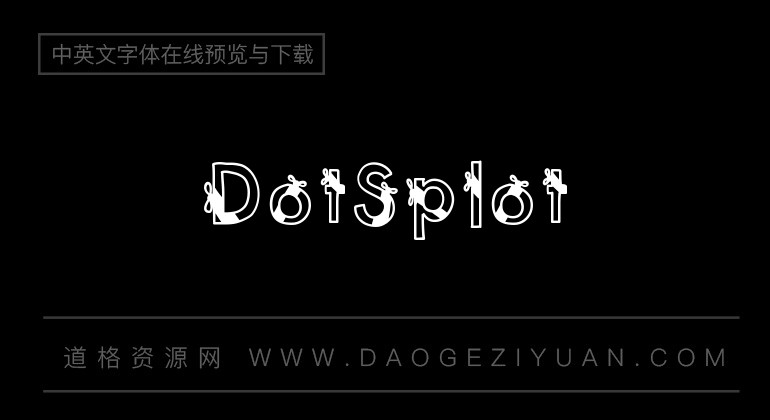
DotSplot 字体是一款由DotSplat设计的超现代抽象字体,它的特点是简洁、现代、抽象,适合用于各类标识、标题、品牌标识等。它采用了精细的细节,使得字体看起来更加精致,更具有视觉冲击力。它的特点是简单、现代而又具有抽象感,可以让你的作品在众多类似的字体中脱颖而出。内容介绍
DotSplot是一款非常不错的手写艺术字体,具有很好的视觉感,适合于文化类的宣传设计、商业类品牌的广告和产品包装设计以及个性化文字排版等较多场景。